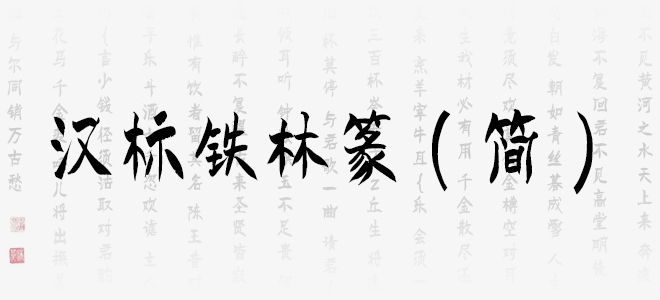
漢標(biāo)鐵林篆(簡)字體巧緣于三國書法家衛(wèi)瓘,衛(wèi)瓘乃王羲之恩師衛(wèi)夫人之伯父,他善隸書、章草,始創(chuàng)柳葉篆,被稱為北派始祖。今鐵林篆來源生活,師法自然,終得字體,是衛(wèi)瓘柳葉篆的傳承,更是對(duì)中華文化的弘揚(yáng)與發(fā)展。作者:段鐵林,德藝雙馨書法家,中國書法家協(xié)會(huì)書法考級(jí)注冊(cè)教師,中國書法學(xué)會(huì)副主席,中國書法美術(shù)研究院副院長等等。歡迎喜歡漢標(biāo)鐵林篆字體的朋友前來下載使用。
漢標(biāo)鐵林篆(簡)